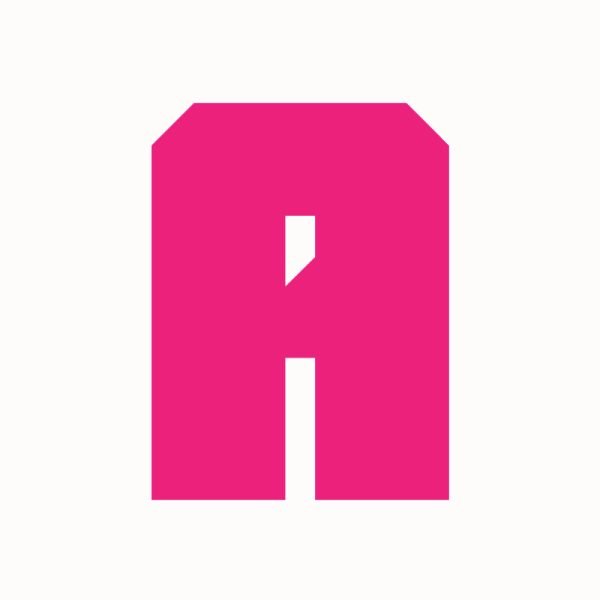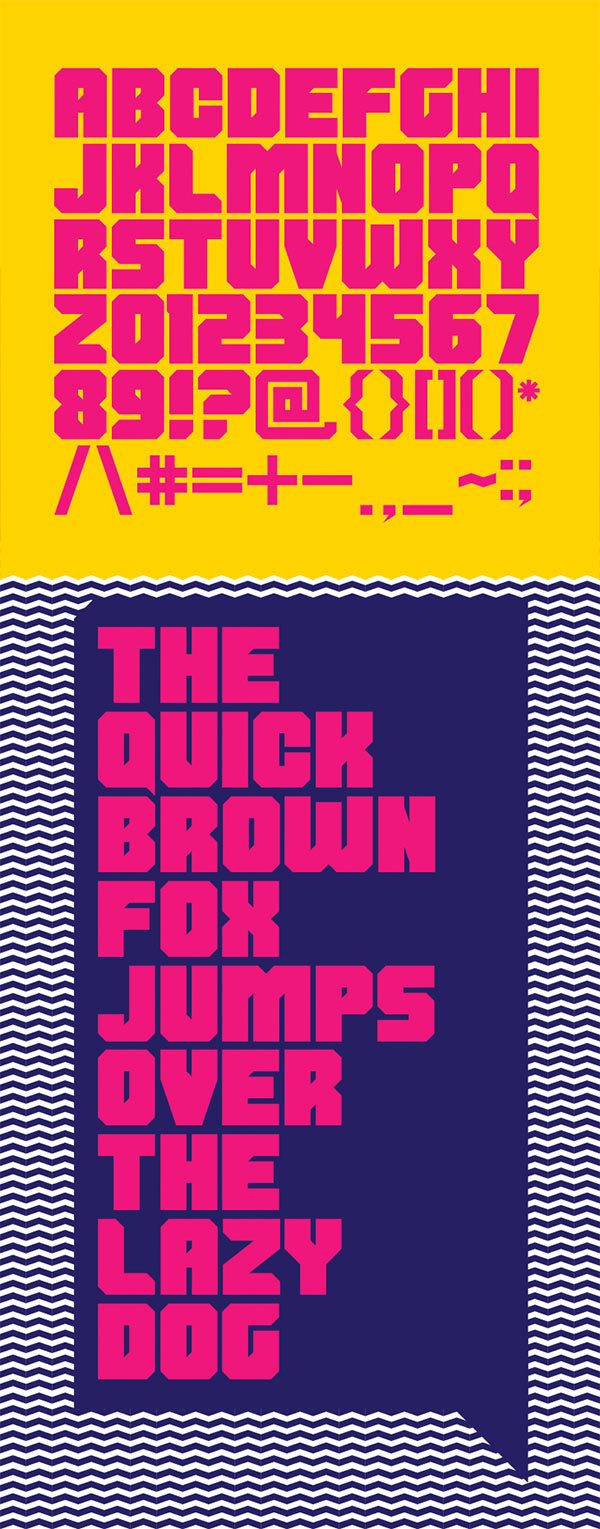
Font del giorno: Shumi Free font
il font che vi presentiamo oggi é:
Shumi
shumi-fullun font pesante e compatto  composta da blocchi di tono utile per creare design dal tocco techno o design espressivi!  la licenza e free per i progeti personali se la utilizzate per progetit commerciali dovrete contattare il creatore Ivan Shumikhin